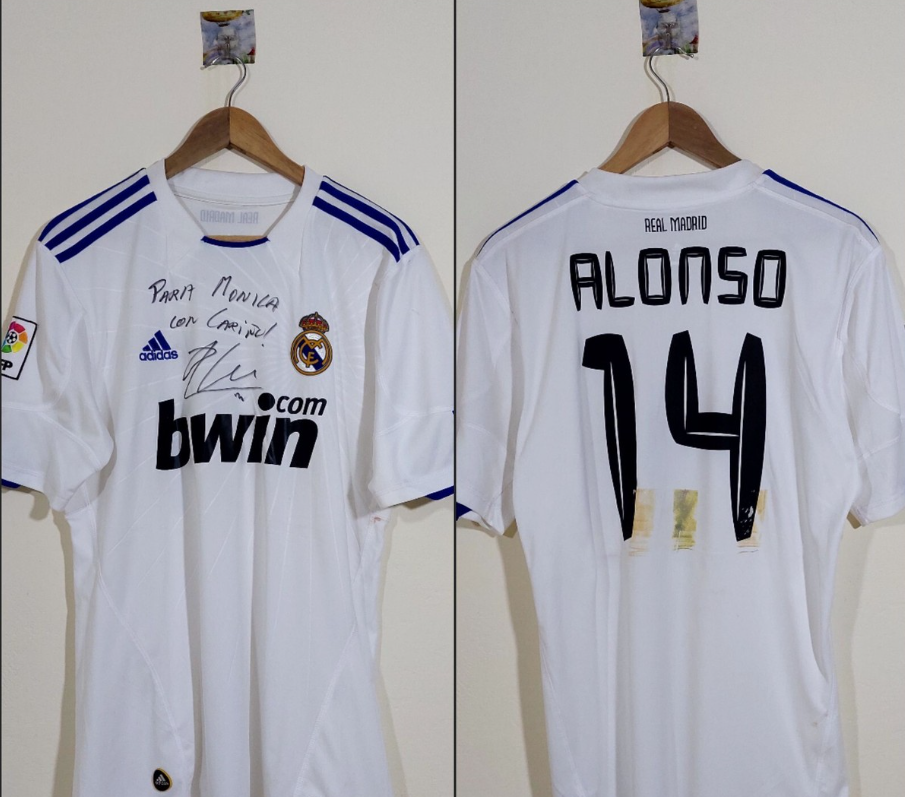
Se você procura nostalgia e classe, acabou de encontrar. A temporada 2010/2011 marcou o início de uma era inesquecível para o Real Madrid sob o comando de José Mourinho. Foi o ano em que vimos lendas como Cristiano Ronaldo (CR7), Kaká, Mesut Özil e Sergio Ramos vestindo o uniforme branco com uma das tipografias mais icônicas já produzidas pela Adidas.
Estilo Visual e Aplicação
A tipografia criada pela Adidas para esta temporada fugiu do padrão “blocado” comum na época. Ela apresenta um design dinâmico, com cortes angulares e um efeito de “sombra” interna nos números, que dava uma sensação de profundidade e movimento.
Esta fonte foi utilizada tanto na La Liga quanto na UEFA Champions League, além da inesquecível final da Copa do Rei contra o Barcelona. O estilo visual remete à velocidade e à agressividade tática daquele time. É a escolha perfeita para quem deseja homenagear a fase em que o brasileiro Kaká brilhava nos gramados do Santiago Bernabéu.